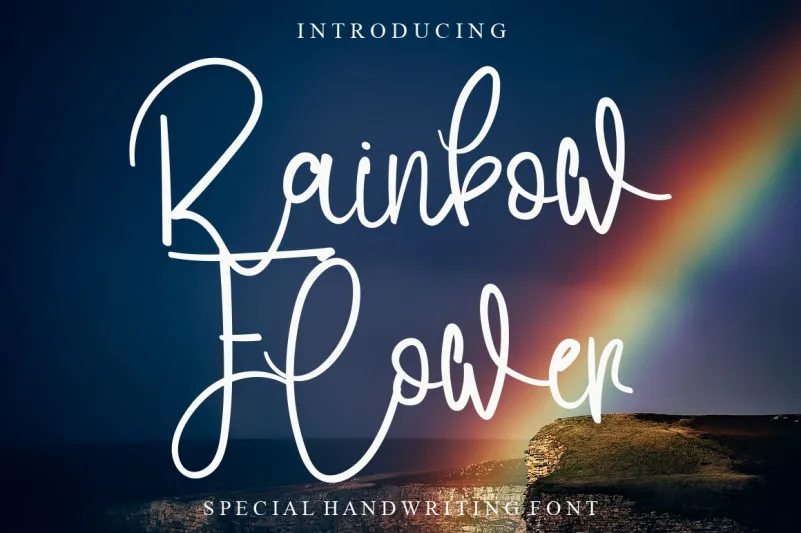
Rainbow Flower Font
A Rainbow Flower Font é uma escolha perfeita para designers buscam uma tipografia que seja tanto funcional quanto estilosa. Esta elegante letra feita à mão possui curvas suaves e levemente relaxadas, tornando-a perfeitamente adaptável para aplicações em moda ou design editorial. Sua facilidade de leitura garantirá um resultado profissional que atende aos mais variados desejos de criação. Desenvolvida pelo designer LevinCreative, a Rainbow Flower Font se destaca por sua fluida e sofisticada natureza, tornando-a uma opção confiável para qualquer projeto onde desejas incluir seu charme único e criatividade. Como uma fonte feita à mão, ela traz um toque de personalização que certamente fará você amar o resultado final.